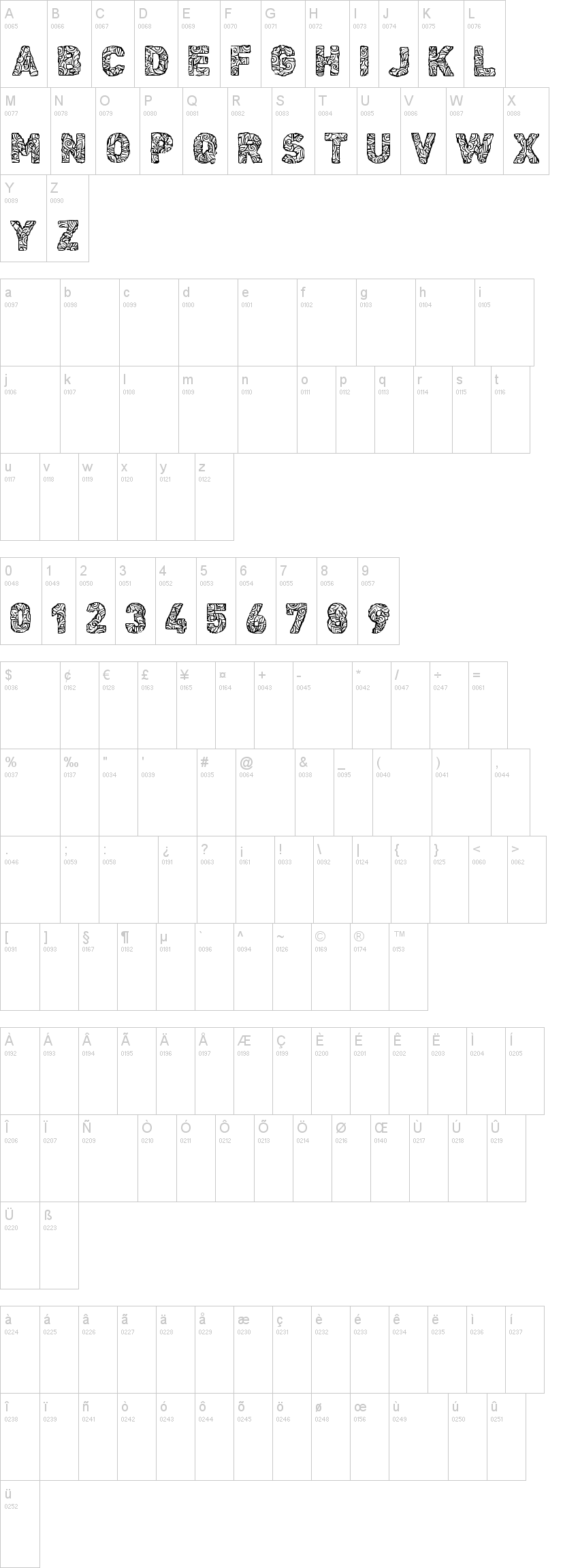
CF Civilisation Maya
CF Civilisation Maya 是一种基于古代玛雅文化的字体。它采用了传统的马雅纹饰,包括类似于太阳、月亮、星星、花卉和动物等图案。这种字体的设计非常复杂,包括了许多细节和线条,非常适合于用于传达古代文明的感觉和氛围。 CF Civilisation Maya 字体非常适合用于设计海报、印刷品、品牌标志和其他需要传达古老和神秘感的设计领域。这个字体的特点是在传达神秘感和古老文明感的同时,还保持了现代感和可读性,因此也非常适合用于数字设计和网页设计。 总的来说,CF Civilisation Maya 字体是一种非常独特和特殊的字体,它非常适合用于传达古代文明的氛围和感觉。
CF Civilisation Maya是一款非常不错的手写艺术字体,具有很好的视觉感,适合于文化类的宣传设计、商业类品牌的广告和产品包装设计以及个性化文字排版等较多场景。